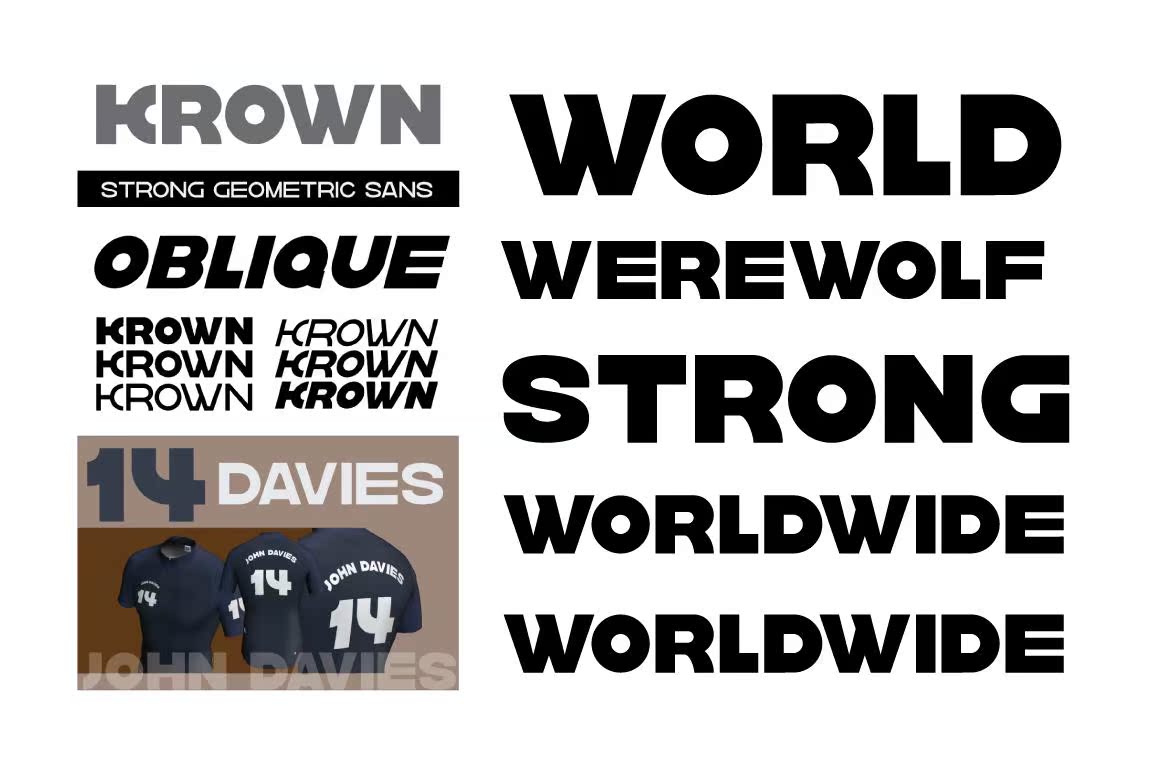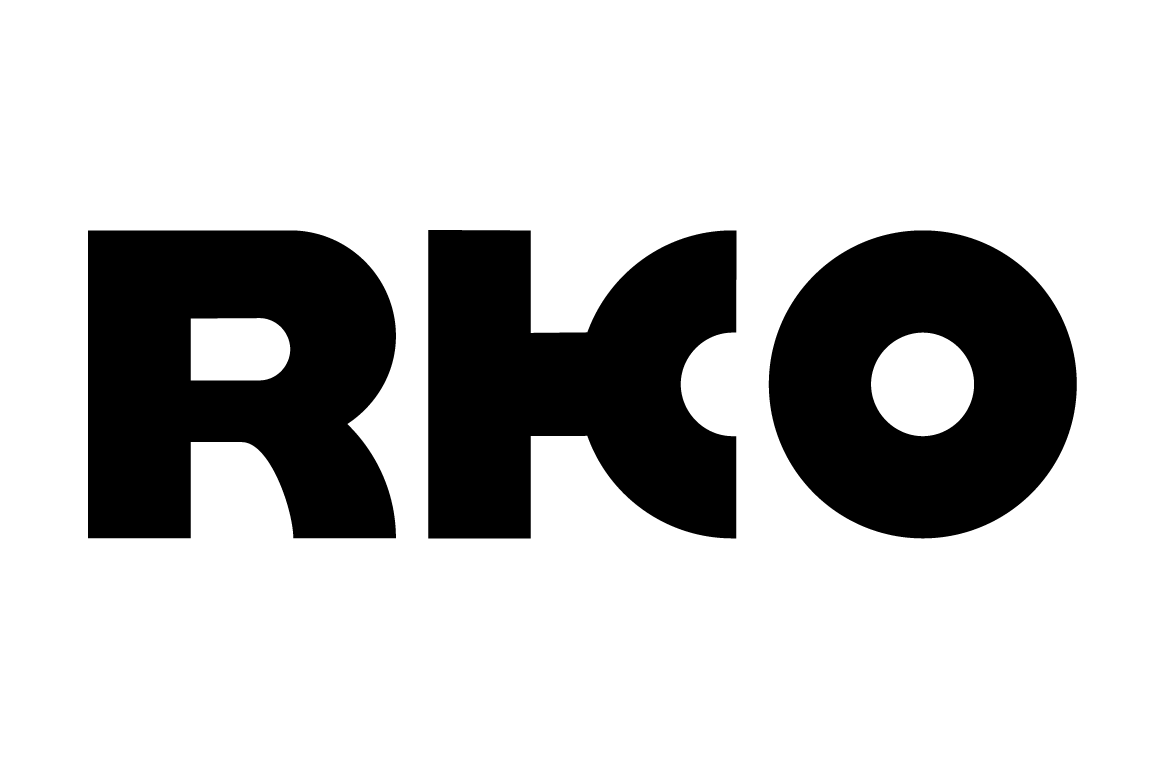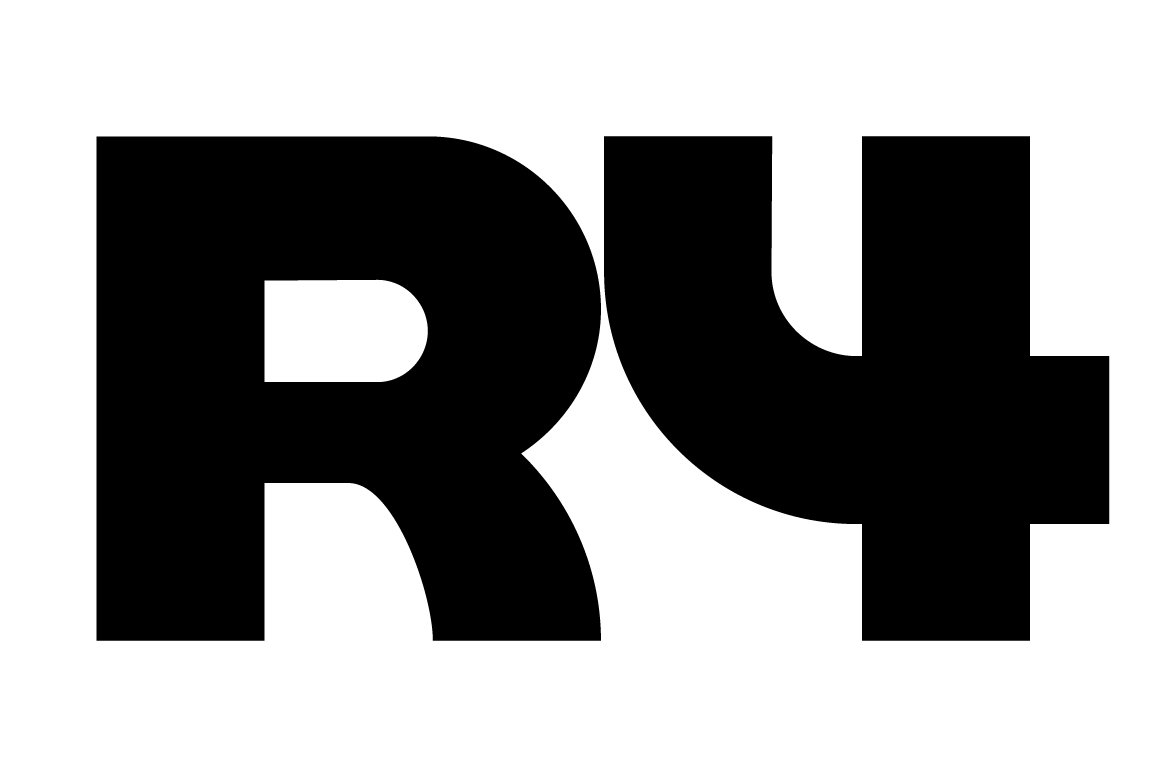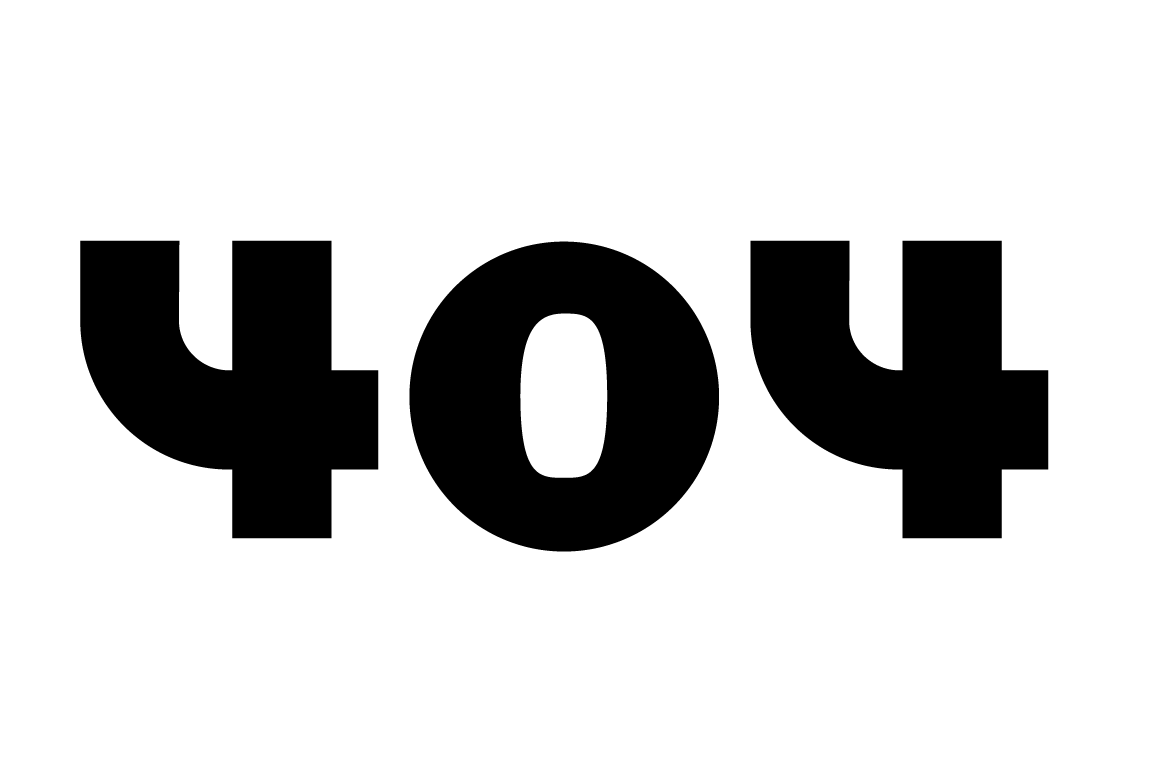
KROWNV1.1具有6种家庭风格的现代化安装几何扫描仪。100%免费供个人使用和商业使用。捐款用于您对本作品的满意程度; sigitnurwicaks@gmail.comfreefontforallyoubigboldfontloversKROWNV1.1aModernStrongGeometricSansSerifwith6famillystyle.100%免费供个人使用和商业使用。捐赠本作品所带来的快乐; sigitnurwicaks@gmail.comfreefontforallyoubigboldfontlovers